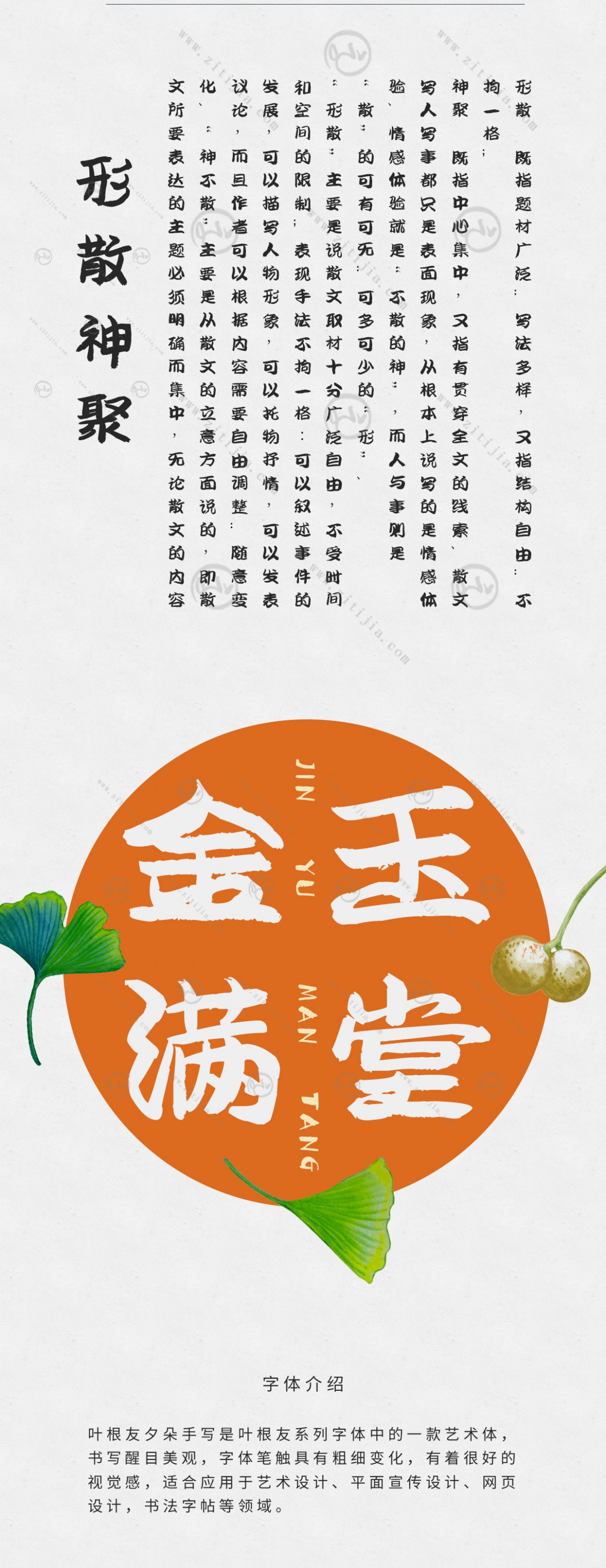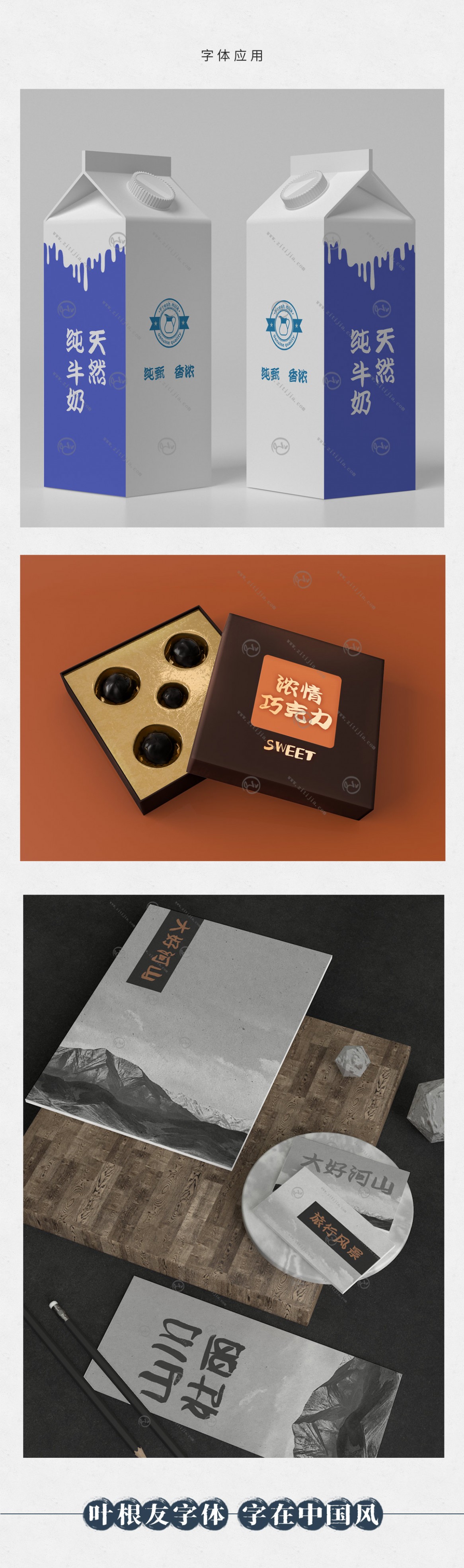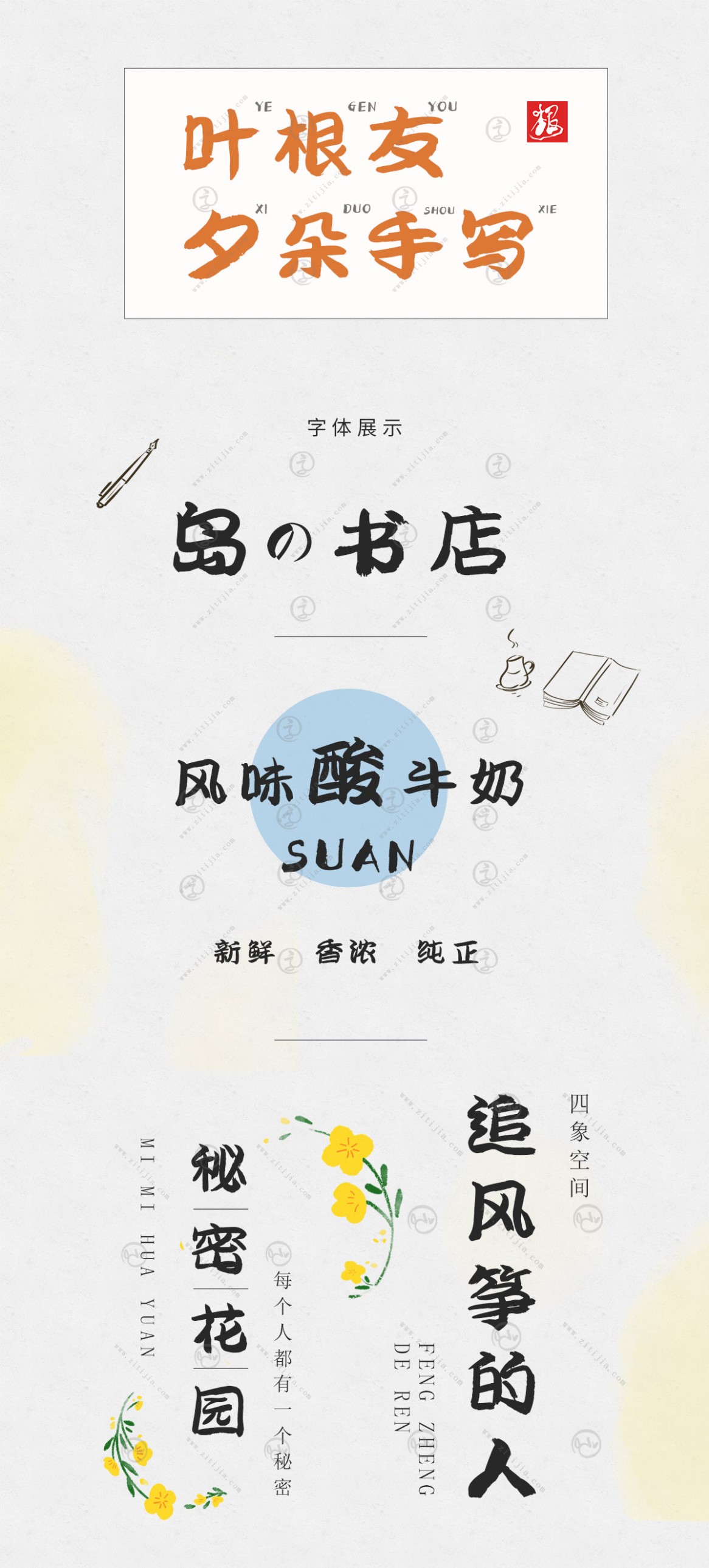
葉根友夕朵手寫
葉根友夕朵手寫是葉根友系列字體中的一款藝術(shù)體,書(shū)寫醒目美觀,字體筆觸具有粗細(xì)變化,有著很好的視覺(jué)感,適合應(yīng)用于藝術(shù)設(shè)計(jì)、平面宣傳設(shè)計(jì)、網(wǎng)頁(yè)設(shè)計(jì),書(shū)法字帖等領(lǐng)域,需要的朋友可以前來(lái)字體家官網(wǎng)下載。